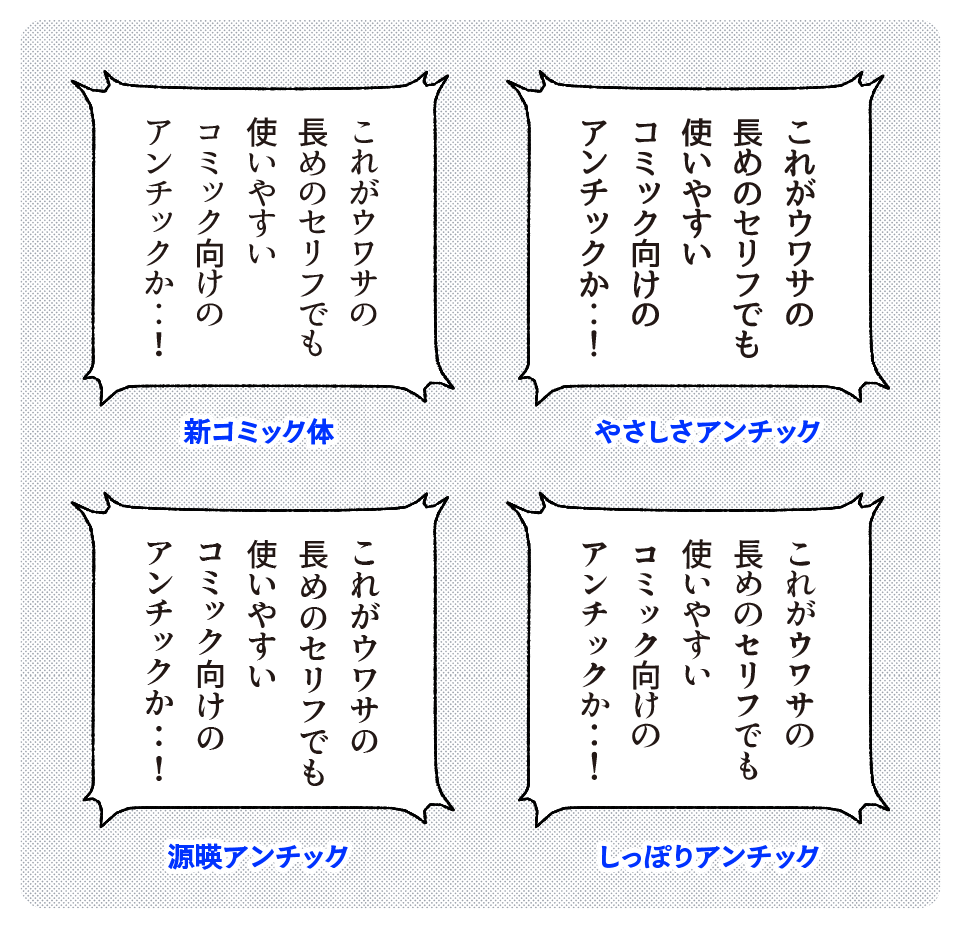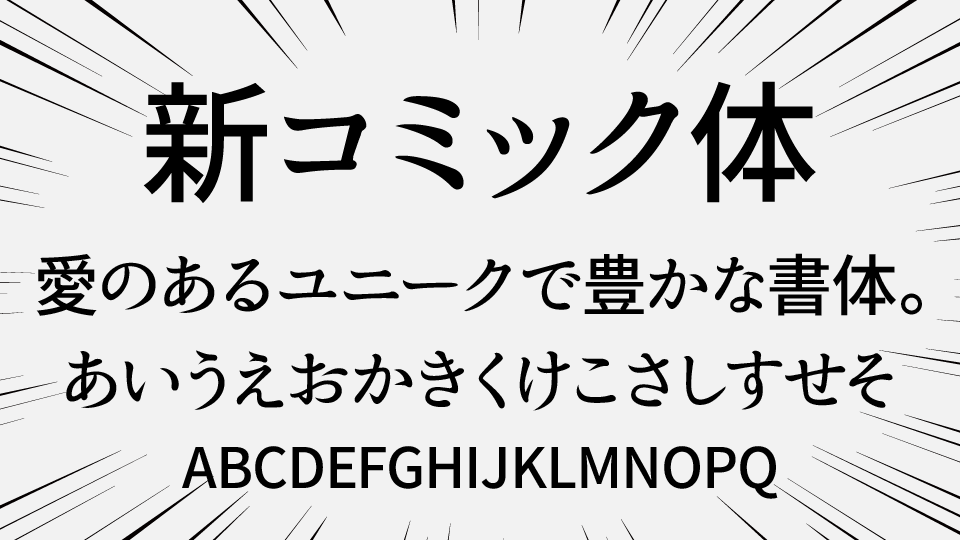
F910新コミック体フォントは、かな仮名文字の特徴を残しつつ、ゴシック体の漢字と組み合わせたアンチックフォントです。
アンチックフォントは、漫画のセリフ文字や吹き出し文字などに取り入れられることが多く、かな文字を明朝体、漢字をゴシック体の組み合わせて作られているフォントです。
フォント作者様いわく「仮名文字は、懐は小さめに抑え、滑らかで上品な曲線を持っています。 組んだときの全体のバランスも綺麗に揃っているようバランスを整えました。」とのことです。
マンガや同人誌を制作されている方には、F910新コミック体は、おすすめのフォントの1つです。
収録文字は、ひらがな・カタカナ・漢字・記号・英数字が収録されています。漢字は「「源ノ角ゴシック」がベースとなっているので、一般水準の漢字は収録されているようです。